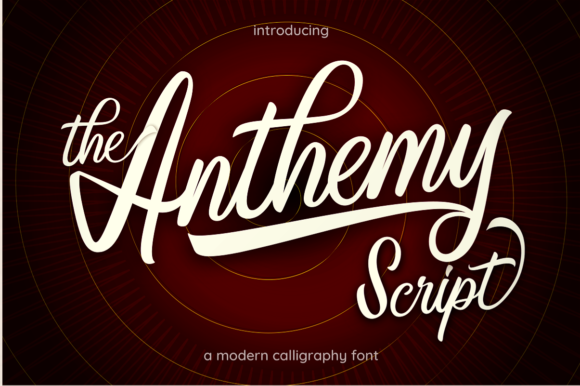
Anthemy - приятный и уверенный рукописный шрифт.
Этот шрифт читается как сильный, уверенный и динамичный и может придать тонны ностальгического характера вашим дизайнерским работам.